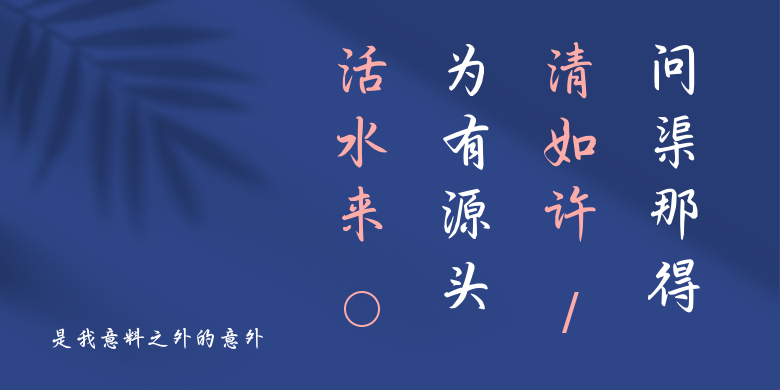
是我意料之外的意外
是我意料之外的意外,这款字体结构工整、笔画清晰,兼顾美观与易读性,适用于标题、正文、海报、包装、LOGO 等多种场景。字形优雅稳定,风格百搭耐看,适配日常排版与创意设计,让文字呈现更舒适、更具质感。是我意料之外的意外一笔一画,皆是细节,以均衡的比例、流畅的线条打造舒适视觉体验,字形端正大气,风格简约现代。无论是商业设计、品牌宣传还是日常排版,都能轻松驾驭,让文字更有格调与力量。是我意料之外的意外字体下载。